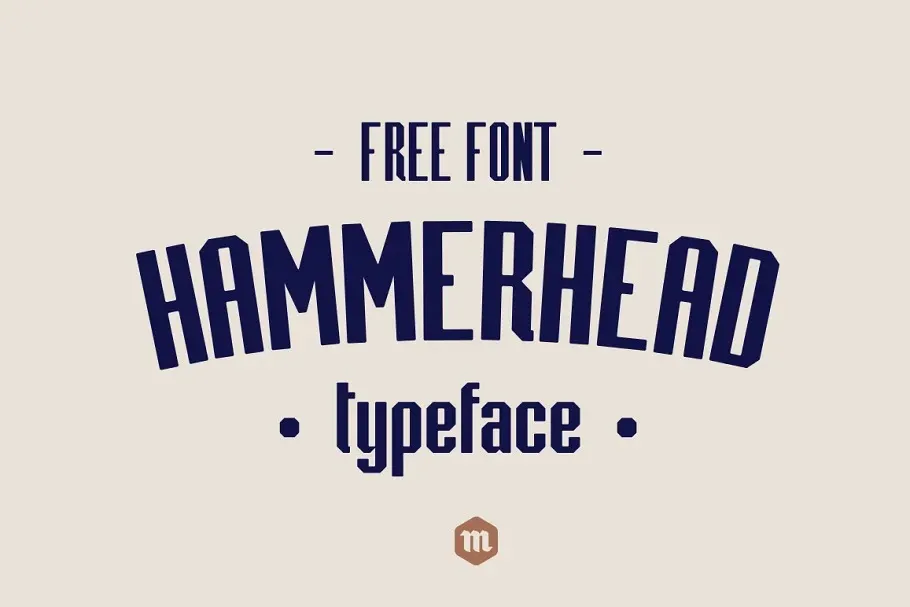
Hammerhead Typeface – Download Grátis
Esta fonte é uma paleta que certamente vai surpreender você. Com esta família de fonts sem serif, terá muitas opções para maximizar suas criações com estilos únicos e modernos. A Hammerhead oferece três pesos: Regular, Condensada e Comprimada, todas com formas letras simples, linhas retas e finais afiados angulados. Cada peso contém 252 caracteres gílios, uma alfabeto maiúsculo e minúsculo, e suporte extenso para scripts latinos. A família Hammerhead abrange um amplo leque de aplicações, mas é perfeitamente adequada para designs de logotipos inspirados em vintage, criação de cartões ou roupas, ou até mesmo textos em bloco ou ocasional. Além disso, a sua elegante simetria e simplicidade fazem da Hammerhead uma excelente escolha para qualquer projeto onde desejar um ar mais sóbrio e moderno é desejado.